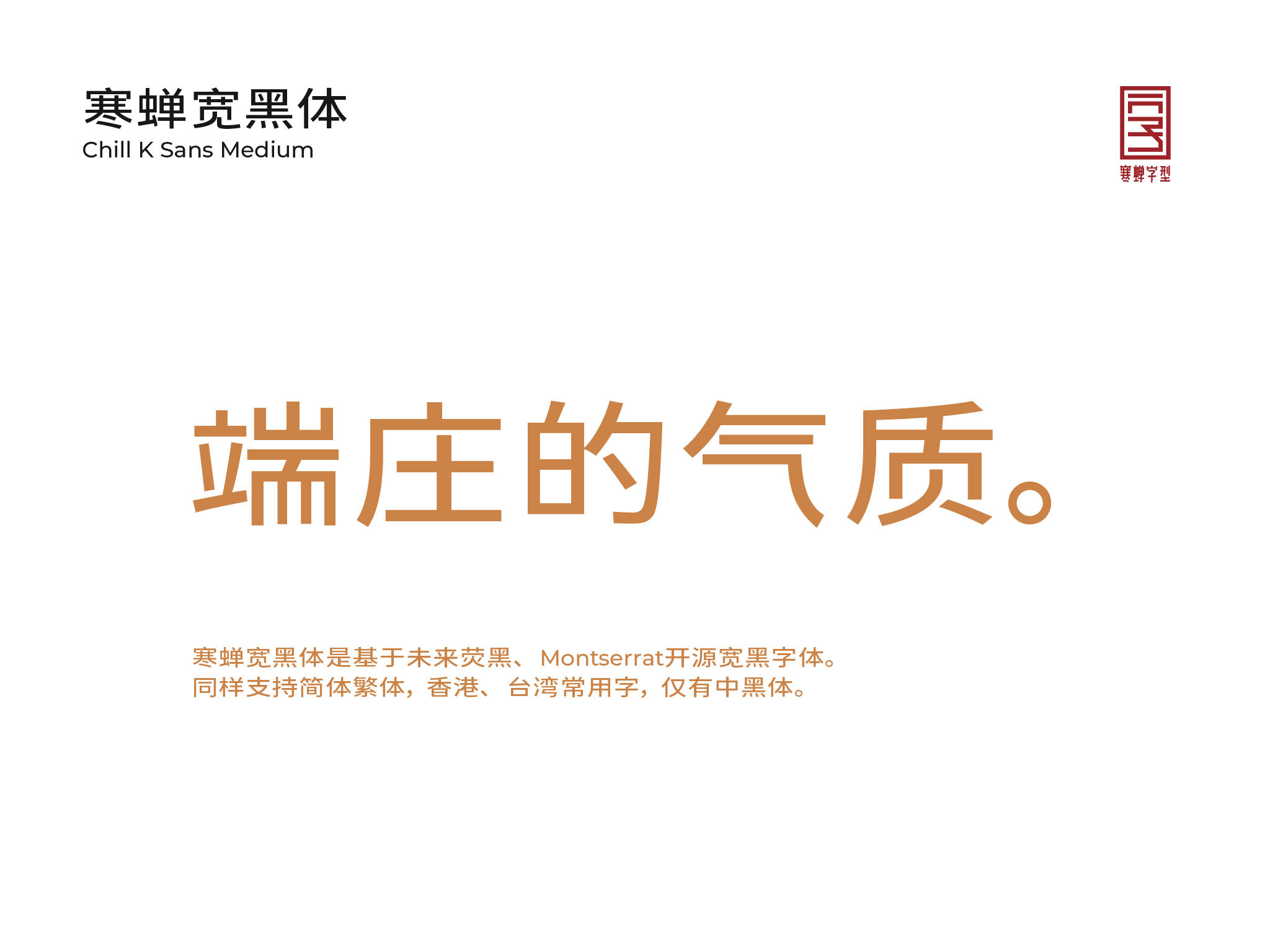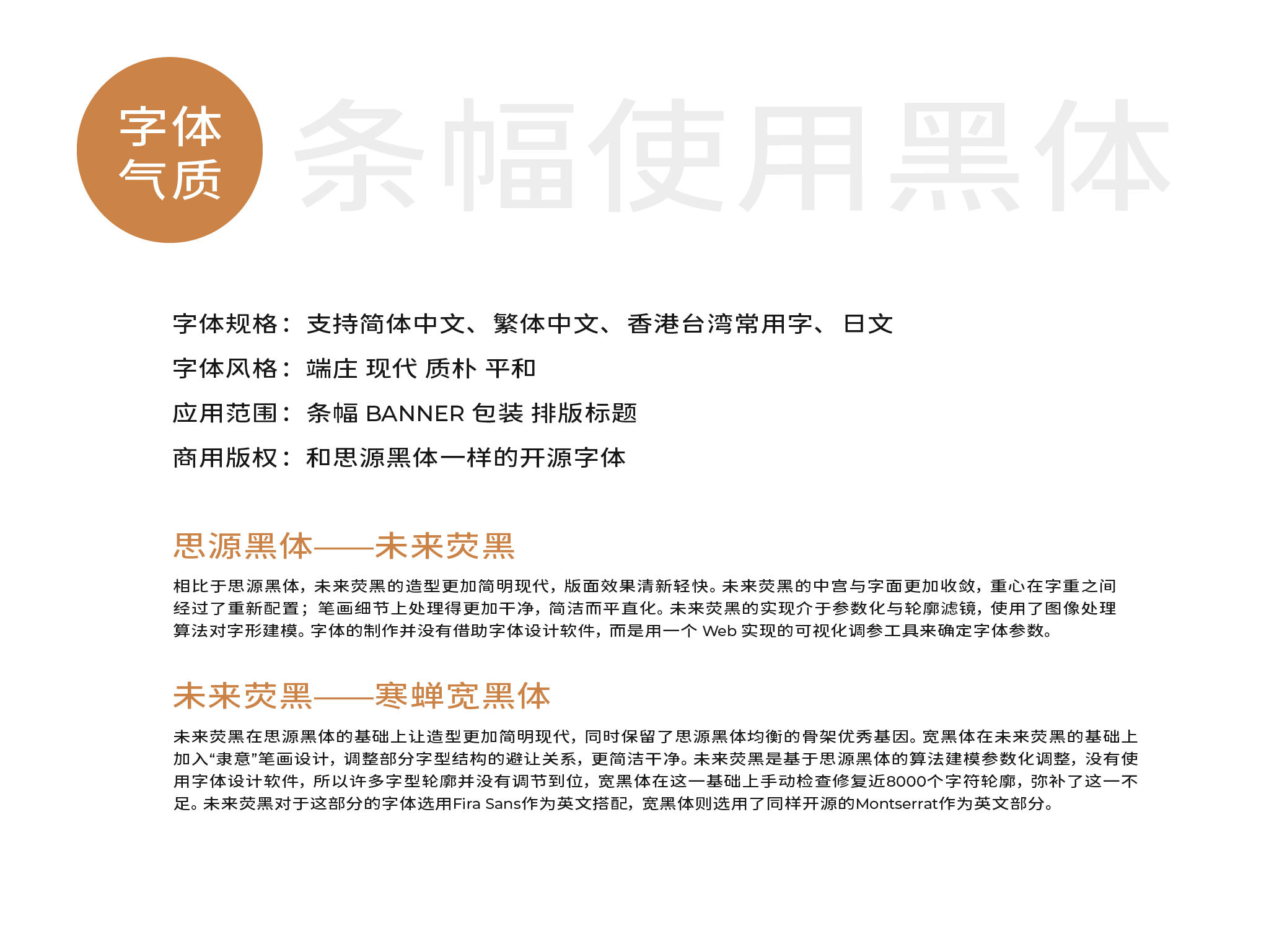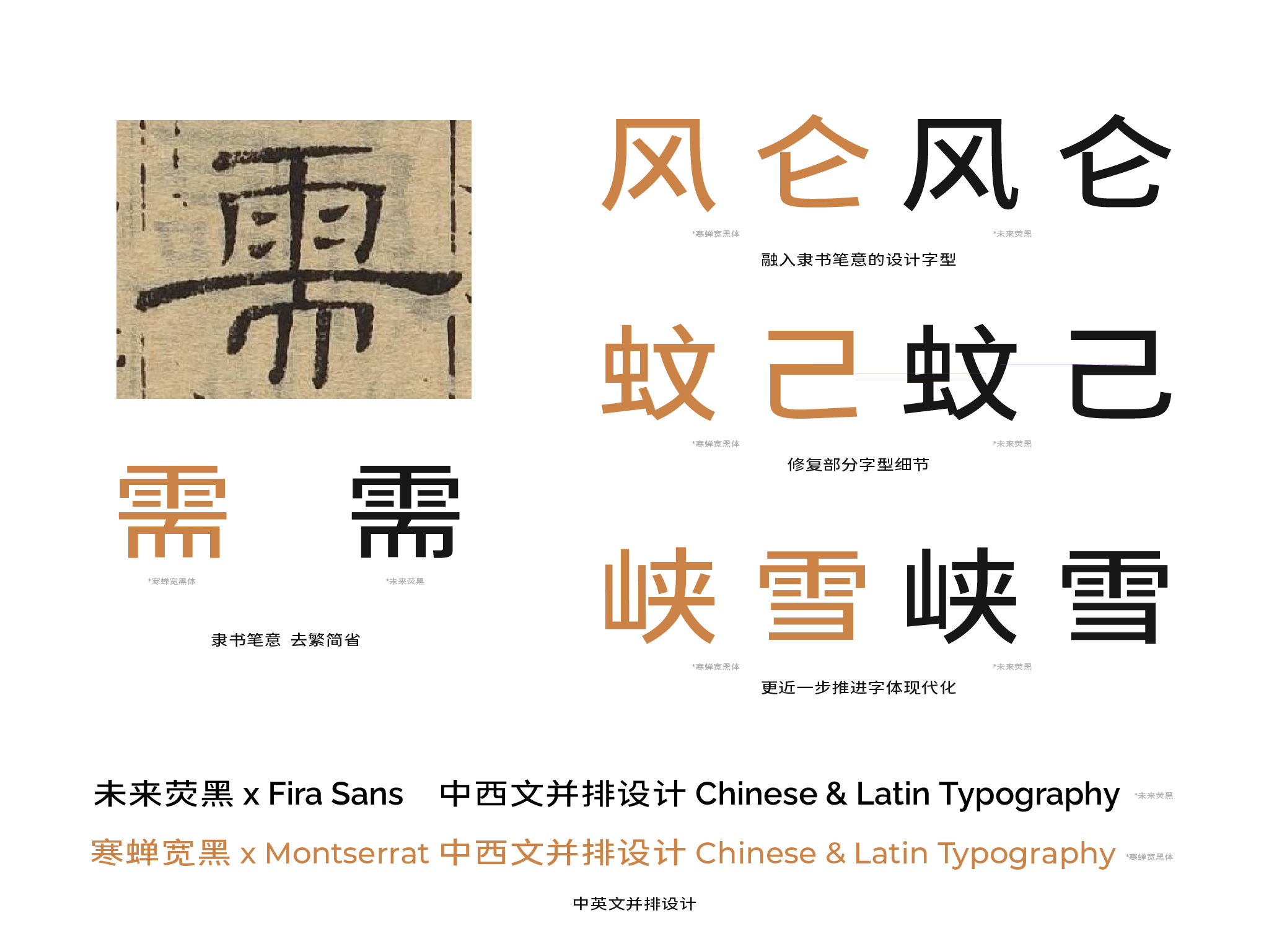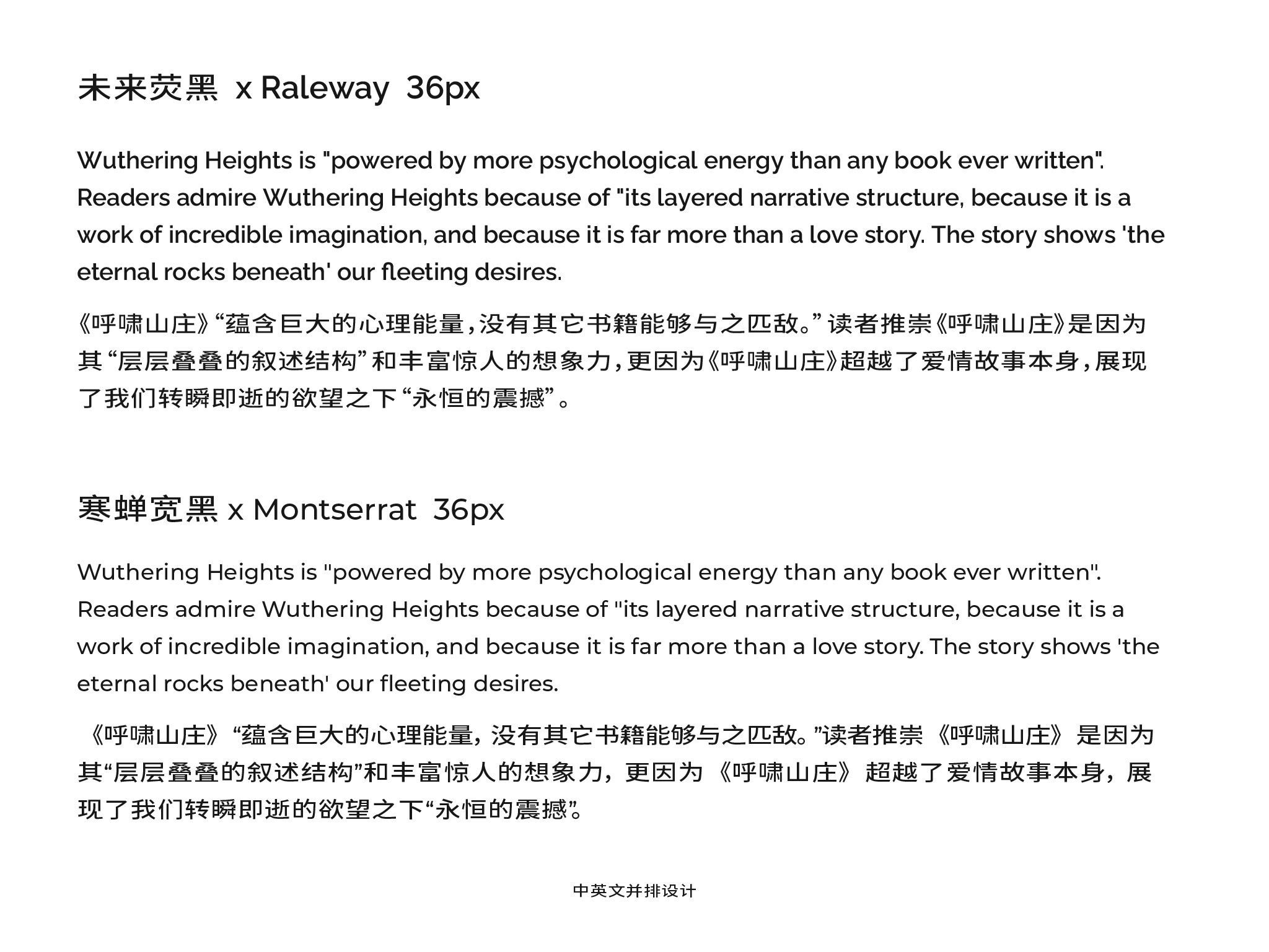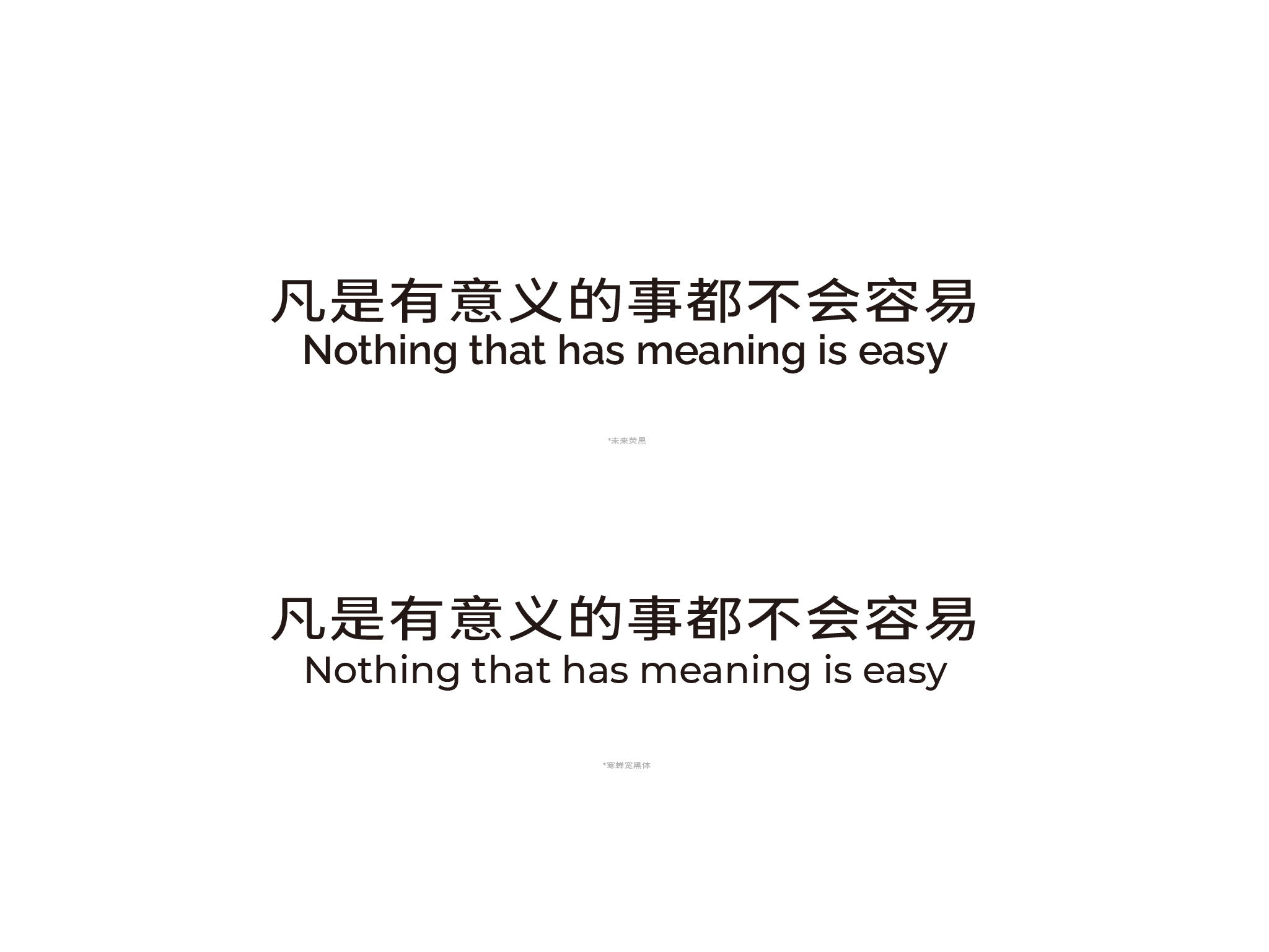
寒蝉宽黑体在未来荧黑的基础上加入“隶意”笔画设计,调整部分字型结构的避让关系,更简洁干净。重新选用了同样开源的Montserrat作为英文部分。
思源黑体——未来荧黑
相比于思源黑体,未来荧黑的造型更加简明现代,版面效果清新轻快。未来荧黑的中宫与字面更加收敛,重心在字重之间经过了重新配置;笔画细节上处理得更加干净,简洁而平直化。未来荧黑的实现介于参数化与轮廓滤镜,使用了图像处理算法对字形建模。字体的制作并没有借助字体设计软件,而是用一个 Web 实现的可视化调参工具来确定字体参数。
未来荧黑——寒蝉宽黑
未来荧黑在思源黑体的基础上让造型更加简明现代,同时保留了思源黑体均衡的骨架优秀基因。宽黑体在未来荧黑的基础上加入“隶意”笔画设计,调整部分字型结构的避让关系,更简洁干净。未来荧黑是基于思源黑体的算法建模参数化调整,没有使用字体设计软件,所以许多字型轮廓并没有调节到位,宽黑体在这一基础上手动检查修复近8000个字符轮廓,弥补了这一不足。未来荧黑对于这部分的字体选用Fira Sans作为英文搭配,宽黑体则选用了同样开源的Montserrat作为英文部分。